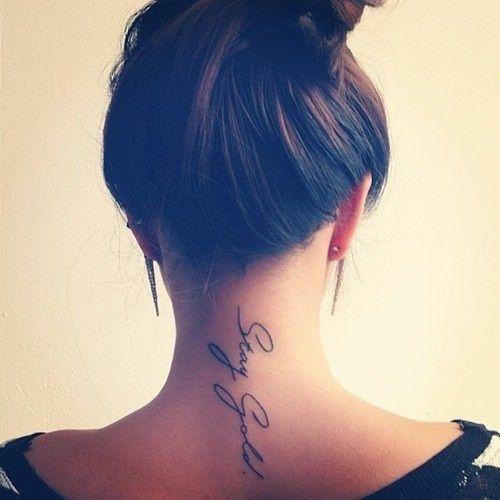
Stay Gold - Suche mich schon dumm und dämlich - bitte Hilfe!
ich suche mich wirklich schon dumm und dämlich, was das für eine Schrift auf dem Bild ist. Leider konnte mir bisher auch niemand helfen. Vielleicht wisst ihr es?
Das Problem, generell bei Tattoos ist, das diese ja mit einem handgeführten "Zeichengerät" auf die "Schreibfläche" gebracht werden. Damit landet selbst dann, hat der für den Schriftzug eine Computerschrift benutzt, nie eine 10% 1:1 Kopie uinter der Haut. Ist der Tattoo-Stecher selbst kalligrafisch begabt, was die doch recht saubere Ausführung vermuten lässt, dann steckt dahiner überhaupt kein Font, sondern der Kunsthandwerker hat seine Vorlage von Hand frei geschrieben.
Generell sollte man ohnehin bei Stechern, die sich ihre Vorlage mit Computerfonts machen müssen eher für Schrifttattoos abstand nehmen, da die Schrift dann oft eher krakelig umgesetzt wird, da sie eben dann nicht aus dem Handgelenk in einem Zug geschrieben wird. Gut das solche Leute dann in anderen Tattoo-Stilen wahre Meister sind, z.B. in bildlicher Darstellung, aber niemand kann wirklich alles.